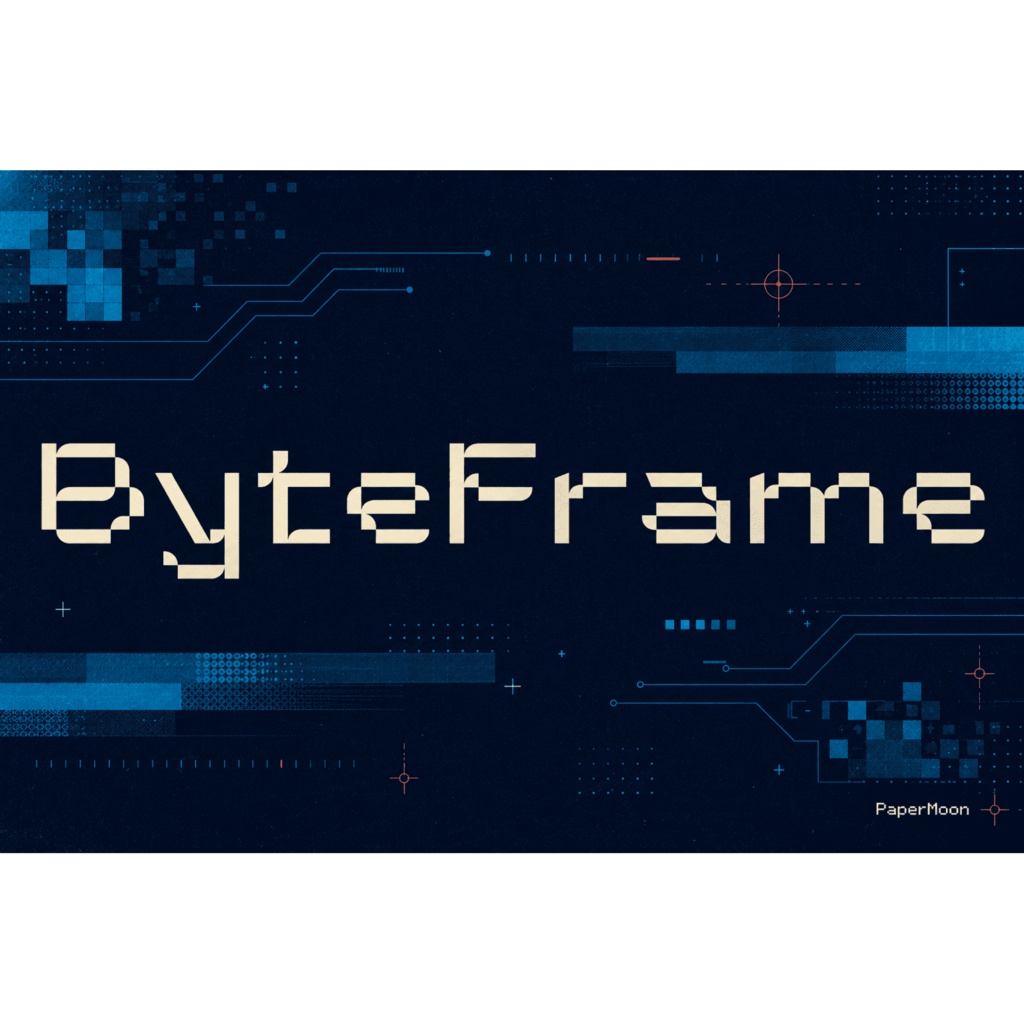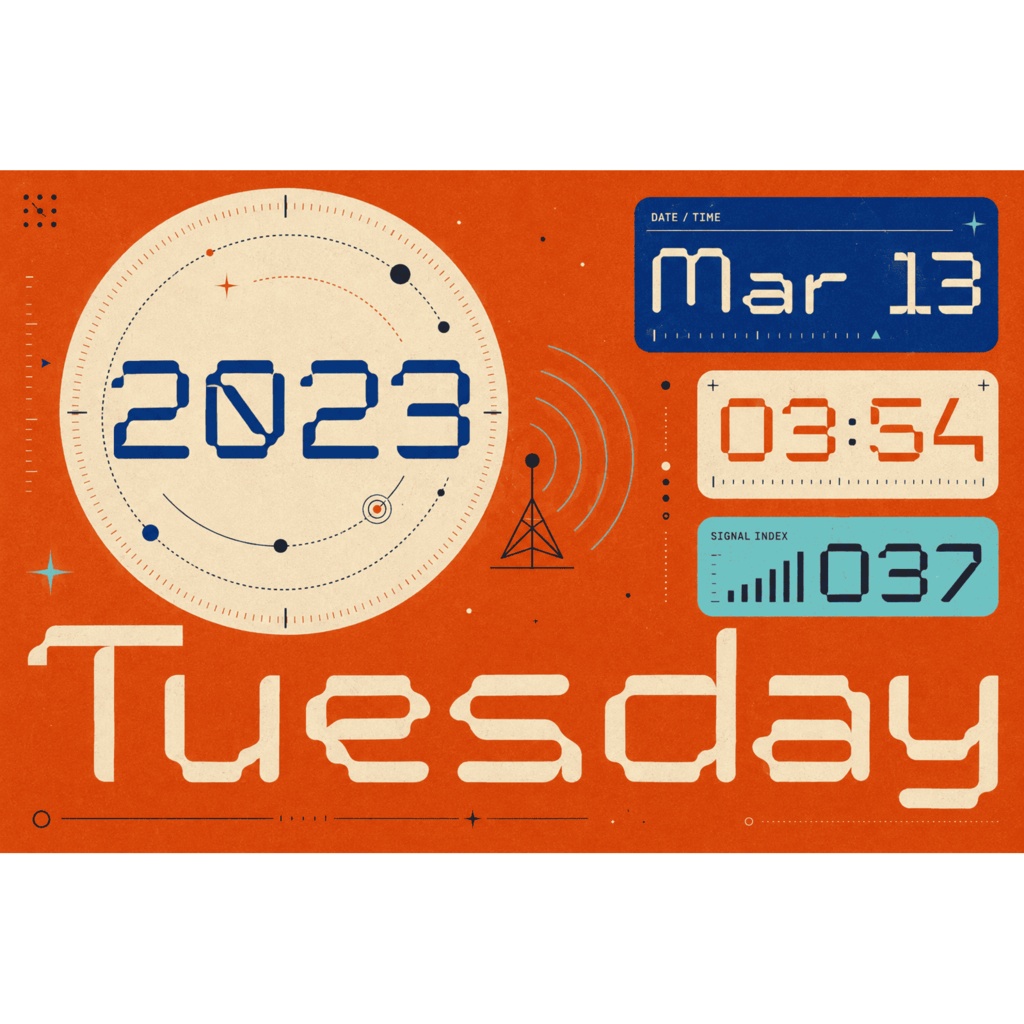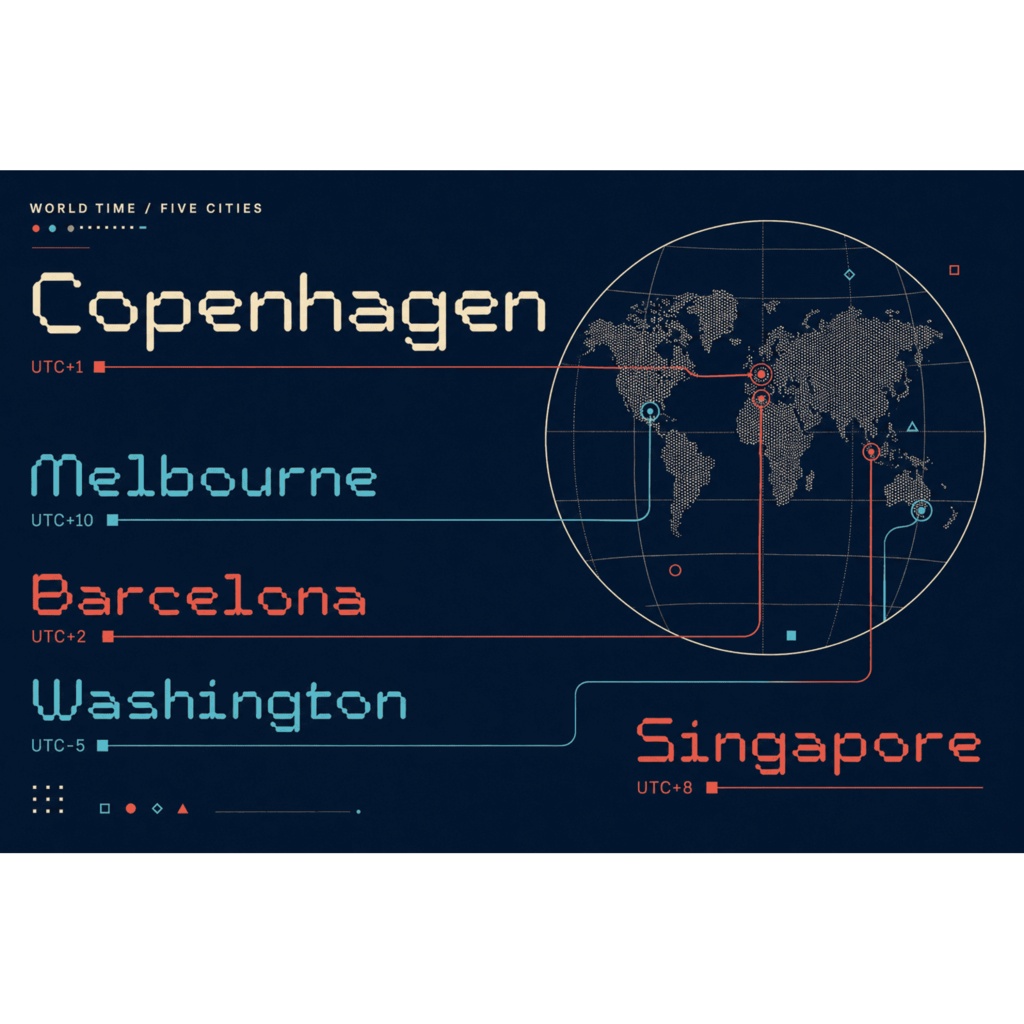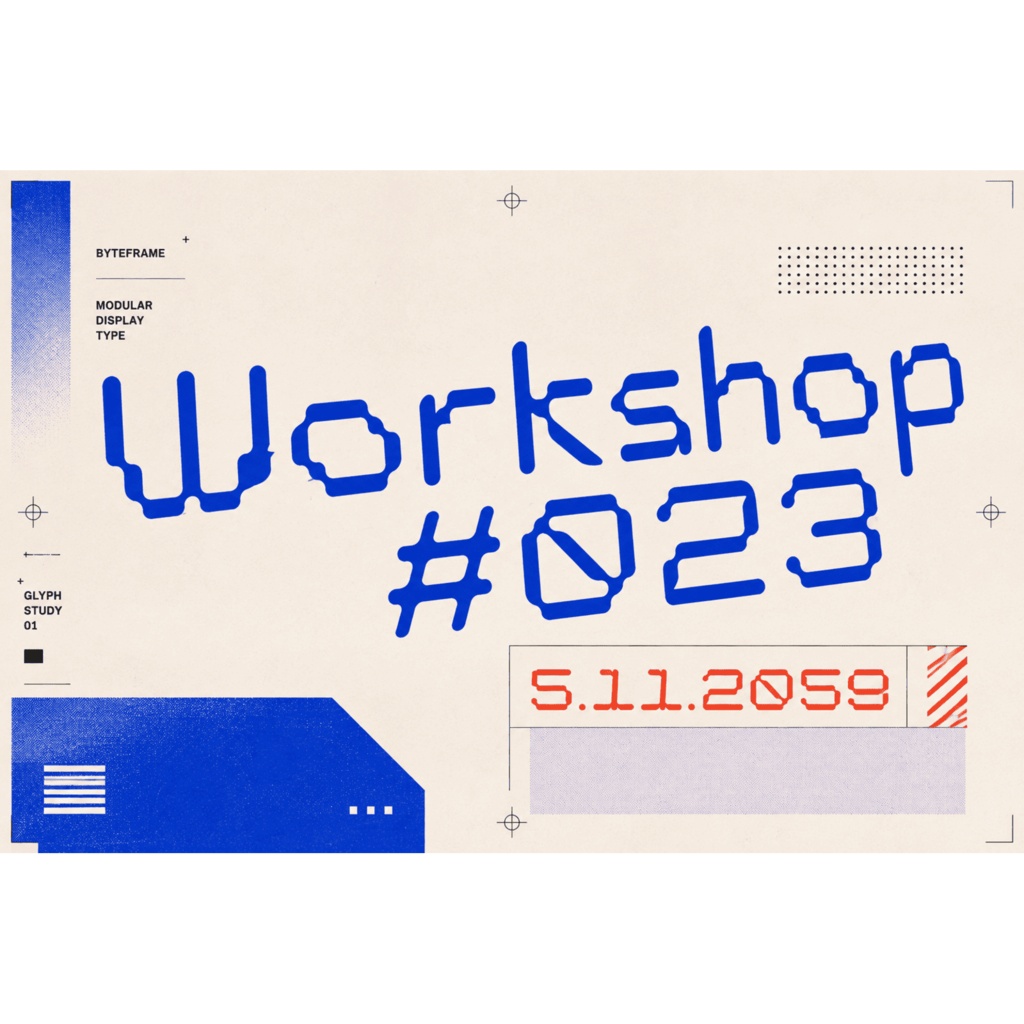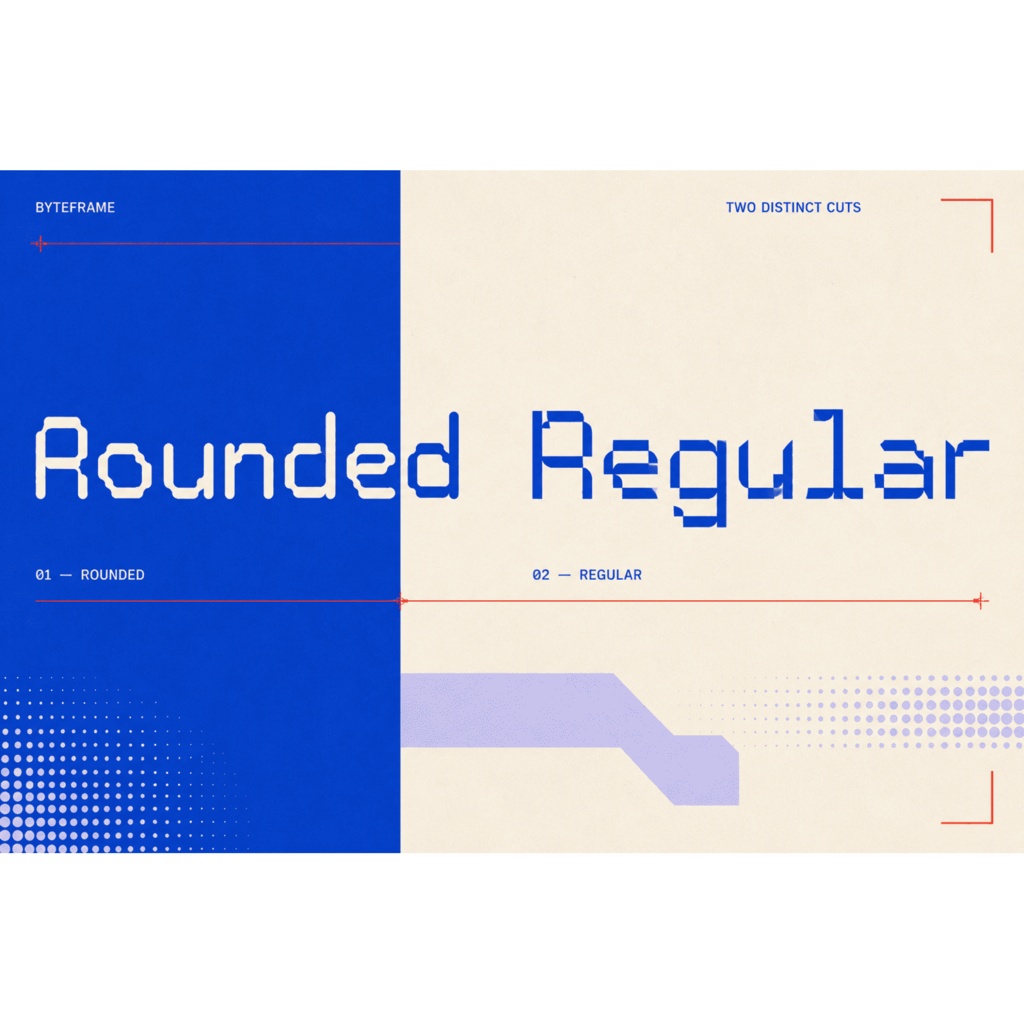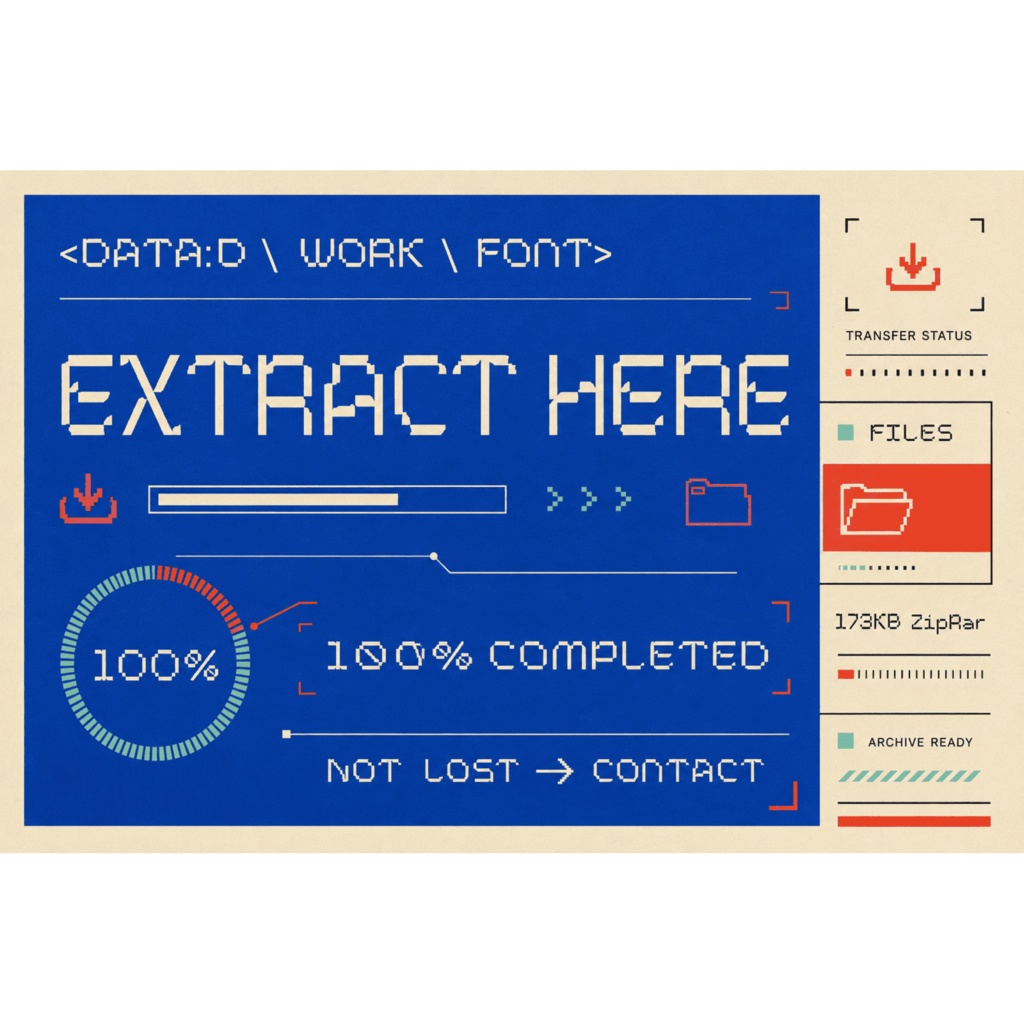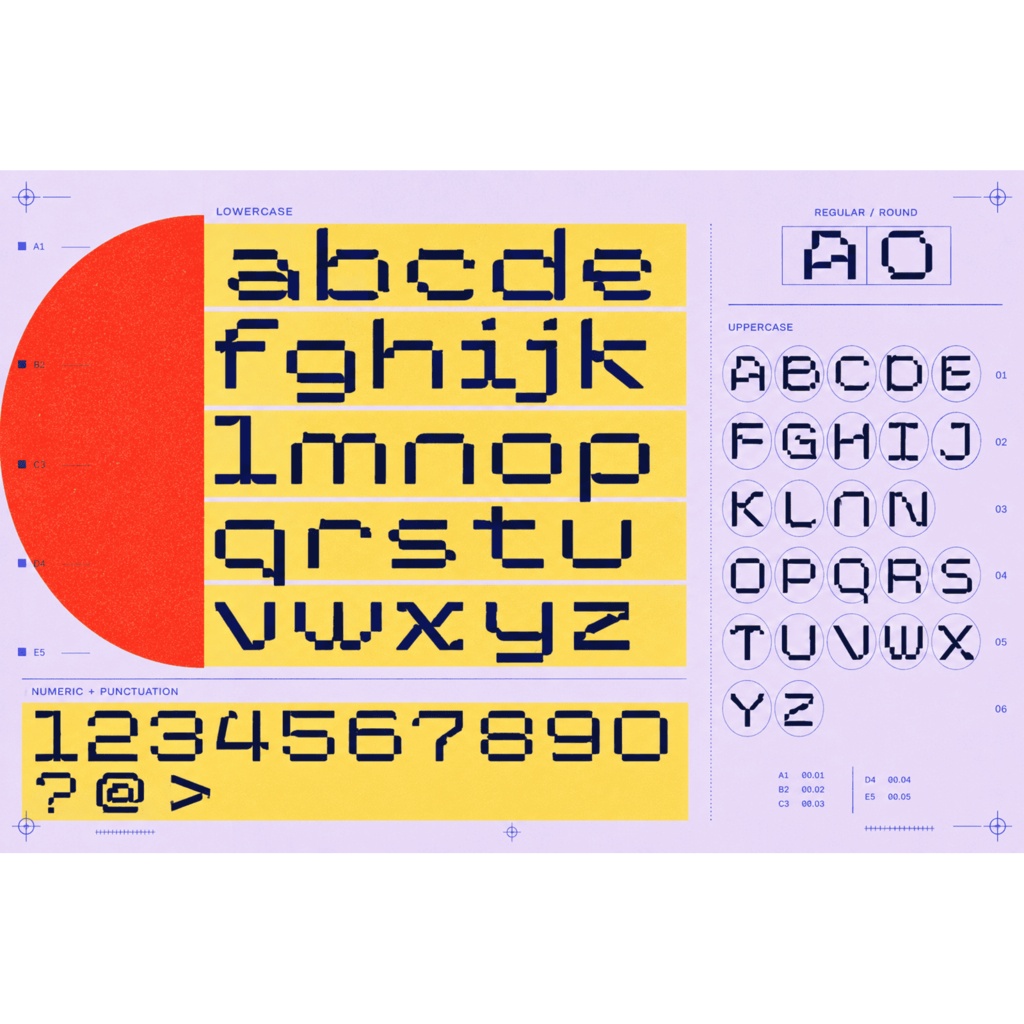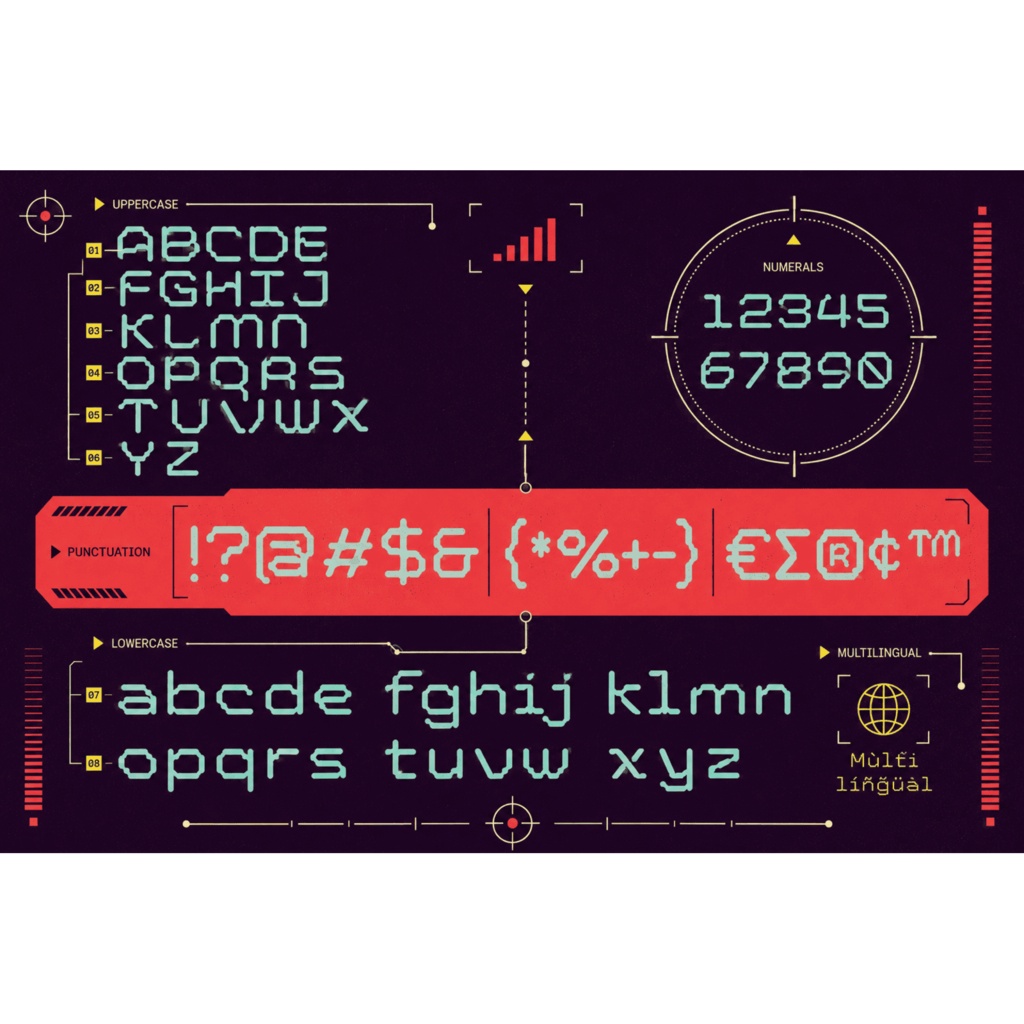
ByteFrame | レトロ8bitピクセルフォント | ゲーム・ロゴ・サムネイル向け
ByteFrame(バイトフレーム)は、8ビットのレトロアーケード感を現代的なデザインに活かせる、モノスペース(等幅)のピクセルフォント(ドットフォント)です。ラテン文字のみの欧文フォントで、シャープな「Regular」と丸みのある「Rounded」の2スタイルを1セットに収録したフォントデュオです。ゲームUI・HUD・ピクセルアート・ロゴ・サムネイル制作まで、幅広いクリエイター用途にお使いいただけます。 収録内容 - フォントデュオ2スタイル:Regular(シャープ・テクニカル)+ Rounded(ソフト・かわいらしい)、全8ファイル - 各スタイル383グリフ。整ったモノスペース(等幅)のピクセルグリッド上に描画され、文字ごとのリズムが揃います 対応文字 - ラテン文字のみ収録:A–Z、a–z、数字、句読点・記号(Basic Latin、Latin-1 Supplement、Latin Extended-A/B)— 西欧・中欧の欧文テキストをカバー - 日本語(ひらがな・カタカナ・漢字)およびキリル文字は含まれません。ラテン文字専用のディスプレイフォントです - OpenType機能:カーニング(kern)、標準合字(liga)、分数(frac)、序数(ordn)、上付き文字(sups)、歴史的異体字(hist)、ローカル形式(locl)、全代替字形(aalt) 用途 - ゲームUI・HUD・インディーゲームのタイトル画面 - ピクセルアート・レトロアーケードのブランディング - テックブランドのロゴ・ワードマーク - YouTubeサムネイル・配信グラフィックス・eスポーツ投稿 - ポスター・アルバムアート・商品パッケージ・グッズ 形式 - ByteFrame-Regular.otf / .ttf / .woff2 - ByteFrame-Rounded.otf / .ttf / .woff2 - デスクトップ・印刷(OTF/TTF)とWeb(WOFF/WOFF2、@font-face)の両方に対応 対応環境 - Windows / macOS。Adobe Photoshop / Illustrator / InDesign、Affinity、Figma、Canva、Procreate、Cricut Design Space、Silhouette Studio など、OTF/TTFを読み込めるアプリに対応。WebではWOFF/WOFF2を使用します 利用許諾 - 商用ライセンス同梱:クライアントワーク、販売用プロダクト、ブランド・マーケティング制作に使用可(出典:本プロジェクトのMasterBundles / Cubebrushリスティング) - 放送・SaaS埋め込み・大量印刷などの拡張利用は、別途の契約が必要です(出典:MasterBundlesリスティング) - フォントデータの再配布・再販や埋め込みの詳細条項は、同梱のライセンスファイルをご確認ください 更新 - フォント名:ByteFrame(ユーザー確定。旧名 AOT Lost Contact は使用しない) - フォントデュオ(2スタイル)、383グリフ/スタイル、モノスペース・ピクセル設計、Copyright (c) 2026 PaperMoon - 本コピーはSEOコピー一式のみ。価格(JPY)・カテゴリ・メディア・パッケージ・出品設定は出品者側で対応してください